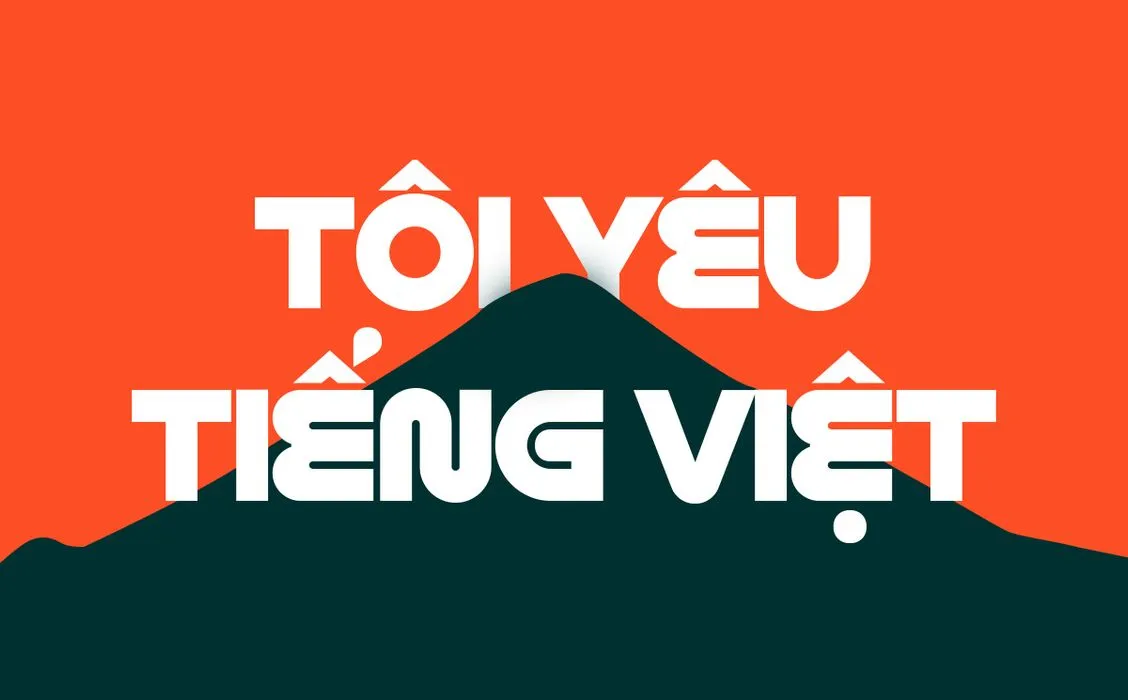
Mission X là một kiểu chữ sans serif vô cùng hiện đại, đậm chất sáng tạo. Lấy cảm hứng từ thế giới thẩm mỹ của Stanley Kubrick và các tác phẩm khoa học viễn tưởng, font này là một biểu hiện tinh tế về chủ đề không gian và công nghệ. Sự tương thích với các thương hiệu và thiết kế hướng tới tương lai và công nghệ cao là điểm mạnh của Mission X.
Đây sẽ là lựa chọn hoàn hảo cho các đạo diễn phim khoa học viễn tưởng, những người đang tìm kiếm một giải pháp thay thế cho Eurostile, mang lại sự hiện đại và độc đáo cho dự án của họ. Mission X không chỉ là một font chữ, mà còn là một công cụ để tạo ra những trải nghiệm độc đáo và tương tác cho khán giả.